Dalam seni tipografi, bentuk huruf sangat mempengaruhi nilai desain. misalnya penggunaan font berbeda pada Judul H1. ketika sudah memasuki isi barulah memakai font standar yang mudah dibaca. kebanyakan desainer, membuat judulnya semenarik mungkin. agar pembaca memiliki ketertarikan walaupun melihatnya sekilas. silahkan baca "15 Aturan dalam seni tipografi".
1. Natyl Font
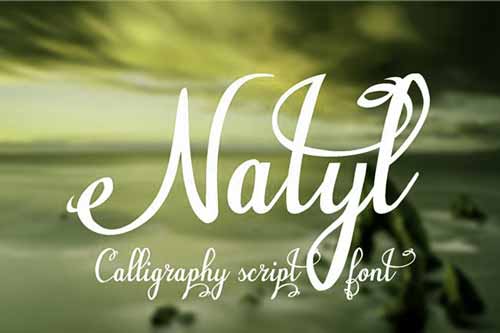
Font Natyl ini termasuk dalam kategori "Kaligrafi" tapi bukan kaligrafi arab. bentuknya yang indah seperti tulisan tangan asli. biasanya creatornya membuat dulu sketsta hurufnya di kertas dari A-Z. kemudian di scan, lalu di olah pakai aplikasi Adobe Ilustrator. terakhir baru di jadikan font utuh.
2. Font Uptown Market
3. Font The Citadel
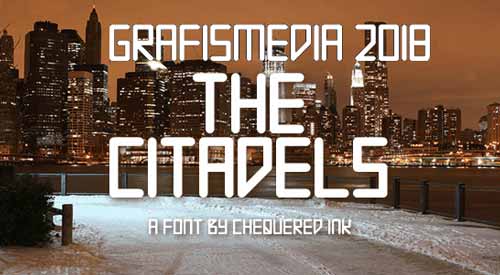
4. Font Paradiso Vintage Demo
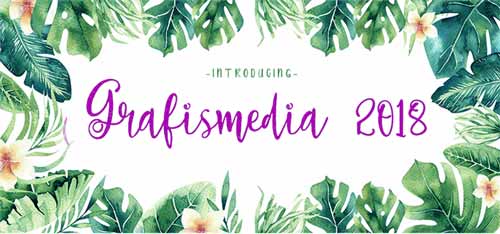
5. Ashley
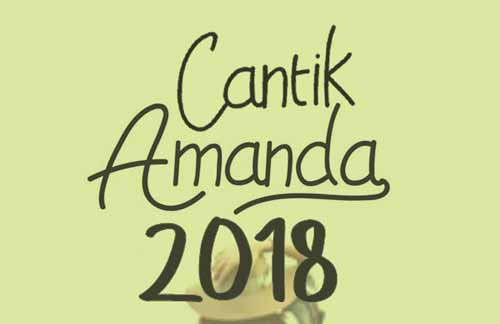
6. Hughs Font
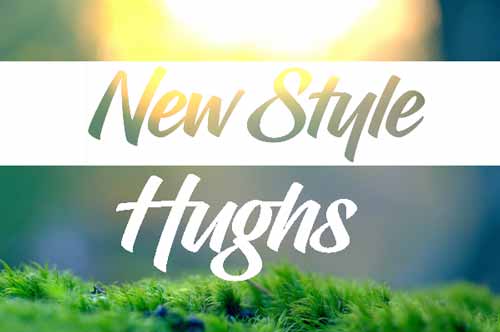
7. Font New Superman
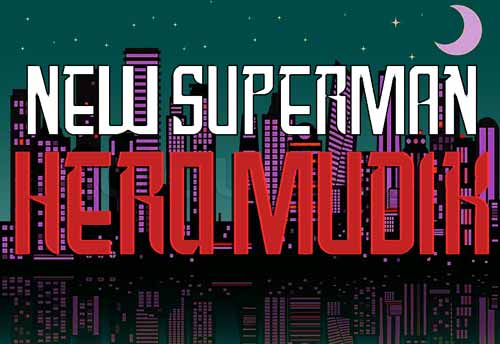
8. Quotus Bold Font
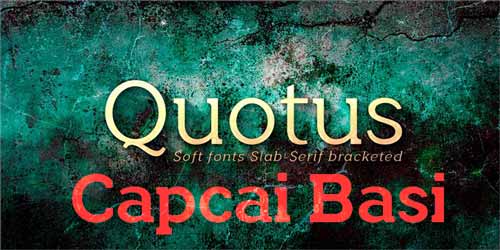
9. Font Harson
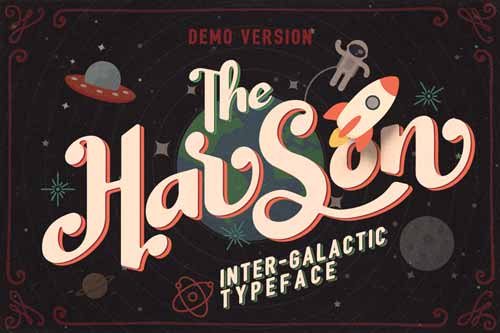
10. Zilap Orion
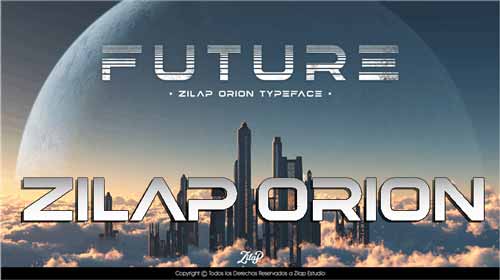
Font Zilap tergolong kategori "'Modern dan futuristik". bentuk hurufnya lebih bergaya masa depan yang erat dengan digitalisme. sangat cocok dipadukan dengan tema desain futuristik.
11. Stika Font
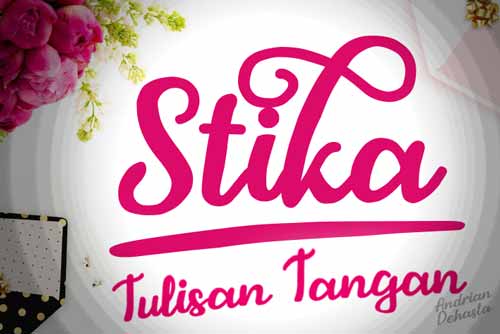
12. Font Hot Legend Team
13. Stay Rad Font
14. Rosse
15. Schwachsin Font
16. Spark Plug Serif Demo Font
Satu lagi font karya anak bangsa, bernama "Irwan wismoyo". dia menjadi salah satu contributor font di situs fontspace.com. font riders gayanya mengarah ke retro atau desain jadul. bukan cuma ini lho ciptaanya. sobat bisa search pakai namanya di fontspace. nanti bisa lihat koleksi dari Mas Irwan.
17. Simple Monologue
18. Sweet Hipster
19. Black Party
20. Easy November
21. Aesthetik Script
22. Muscat
23. Kiraly Font
24. Harlem Deco
25. Simple Stitch
Diantara semua font diatas, yang paling unik adalah Font Simple Stitch. soalnya setiap huruf terbentuk dari sekumpulan "x", atau bentuk jahitan silang. jadi nuansanya lebih ke pakaian atau fashion. bila kalian sedang desain bertemakan konveksi, bisa coba pakai simpe stitch.